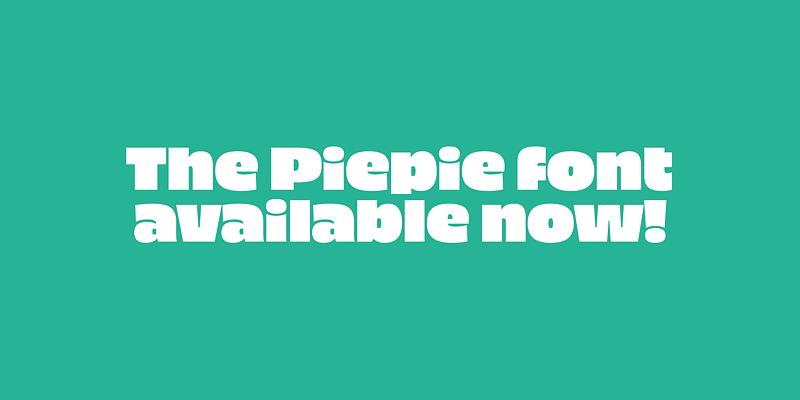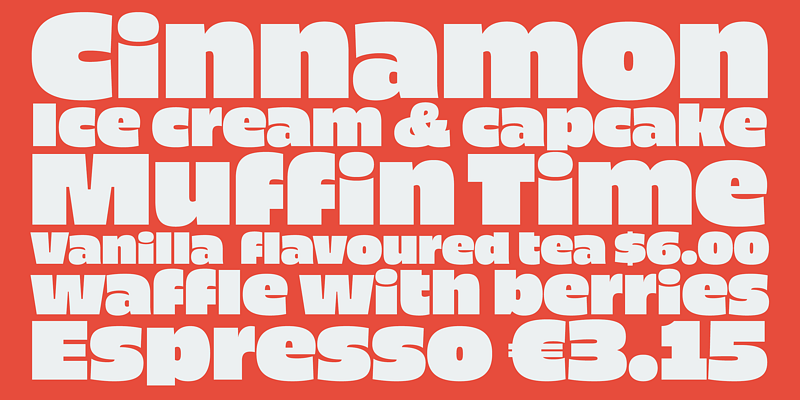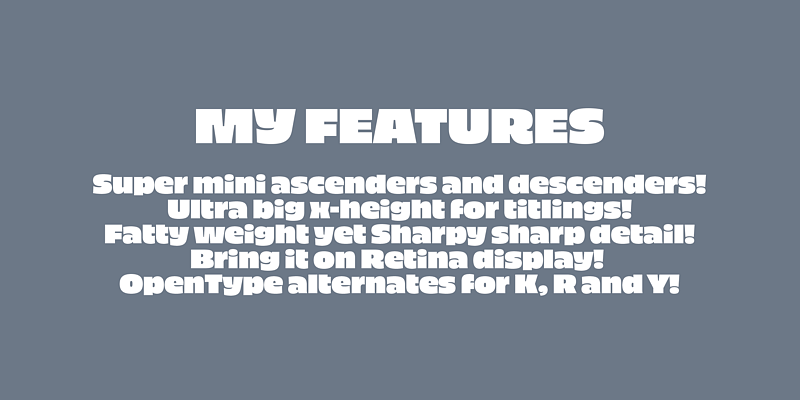
Piepie est une police de caractères très lourde pour les titres et les légendes. De superbes mini jambages inférieurs et supérieurs ! Hauteur d’œil ultra élevée ! Poids gras mais détails ultra-pointus !